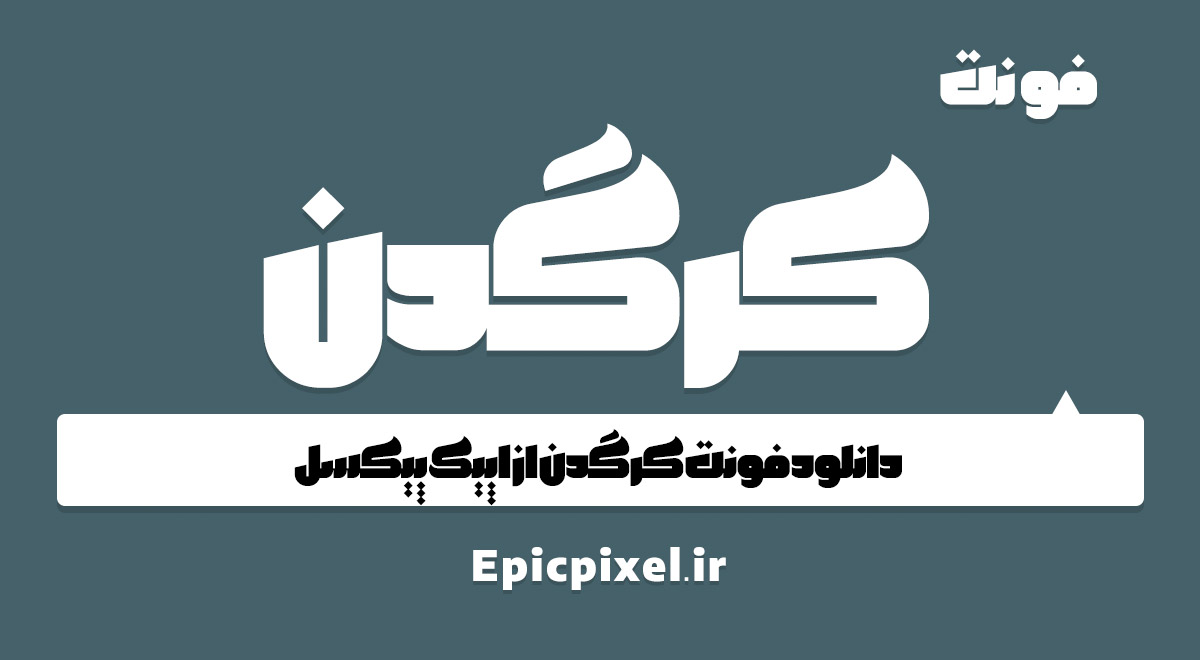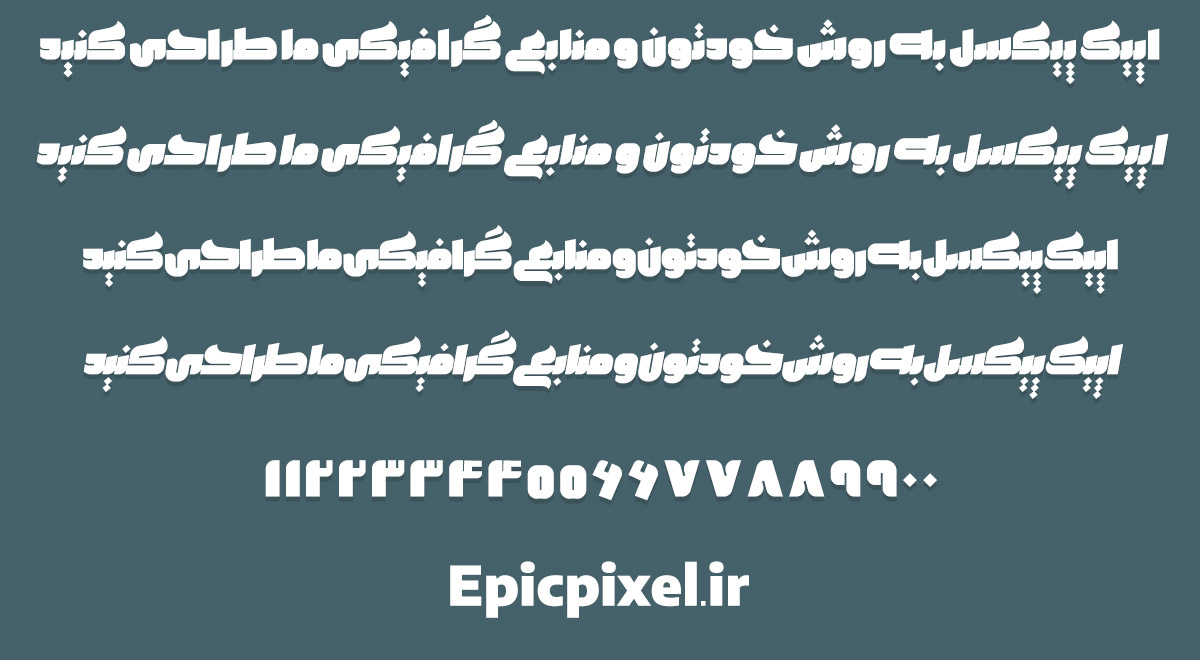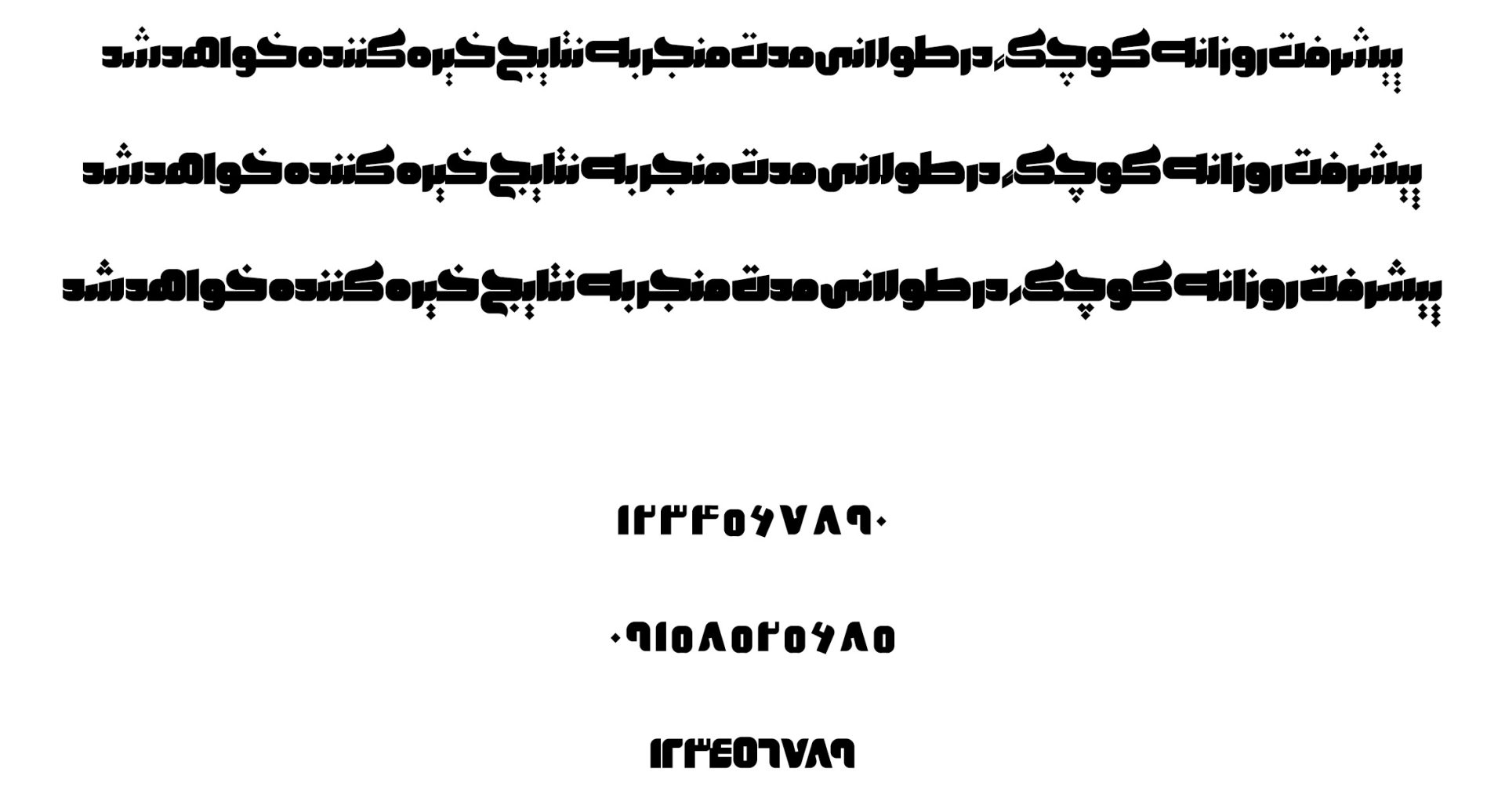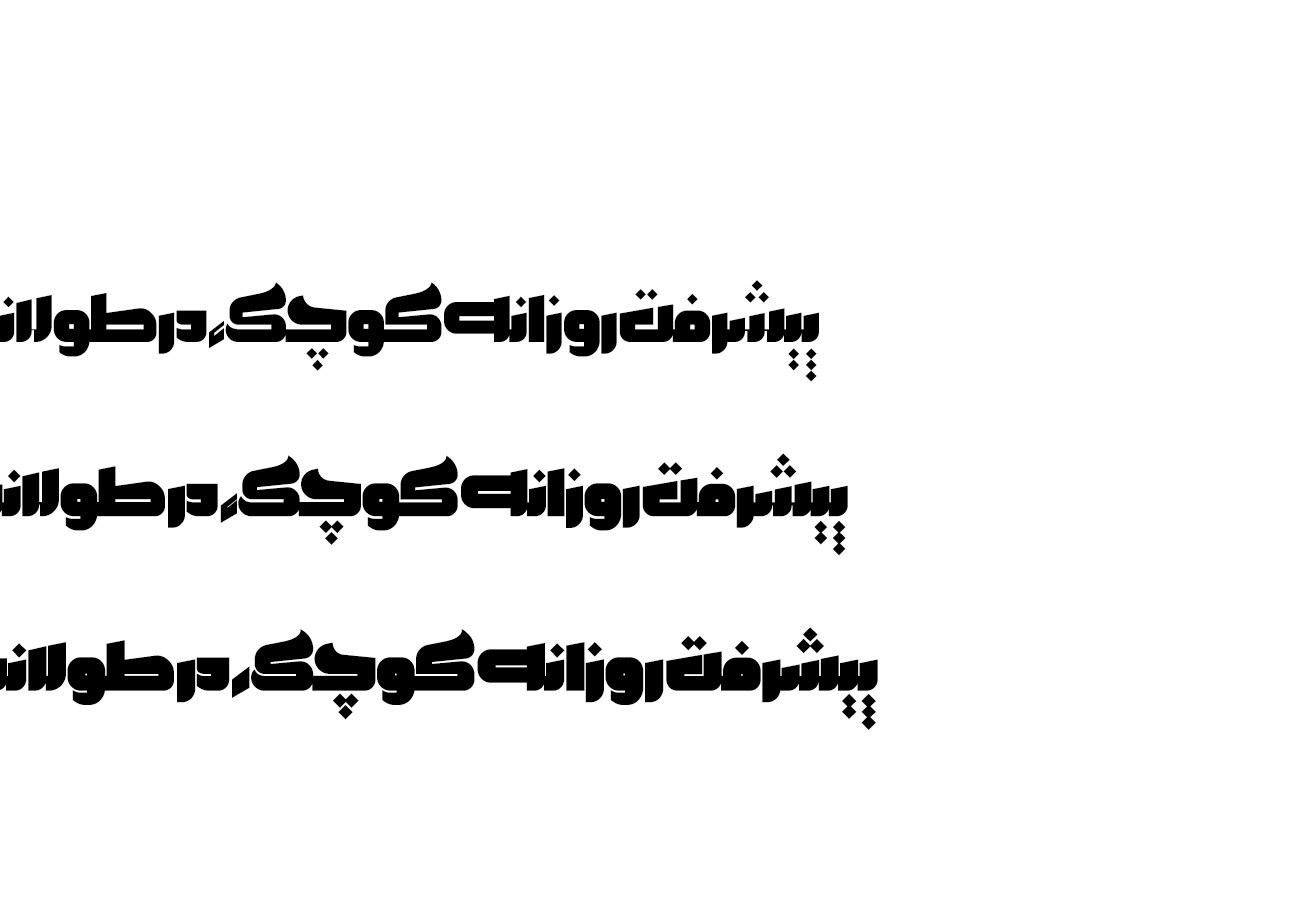
3 فونت کرگدن فارسی
فونت کرگدن فریاد قدرت و اصالت در دنیای تایپوگرافی
فونتهای فارسی زیادند، اما معدودی از آنها با یک نگاه، توجه شما را جلب میکنند و در ذهنتان ماندگار میشوند. فونت کرگدن، یکی از همین فونتهای خاص و جسور است که با الهام از قدرت و اصالت این موجود باشکوه، دنیای تایپوگرافی فارسی را تحت تاثیر قرار داده است. در این مقاله، به سفری در دنیای فونت کرگدن میرویم تا با ویژگیها، کاربردها و تاثیرات آن بیشتر آشنا شویم.
ویژگیهای برجسته فونت کرگدن بیش از یک فونت زیبا
فونت کرگدن، صرفا یک فونت خوشتراش و زیبا نیست؛ بلکه مجموعهای از ویژگیهای منحصر به فرد را در خود جای داده است که آن را از سایر فونتهای فارسی متمایز میکند. برخی از مهمترین ویژگیهای این فونت عبارتند از:
خوانایی بالا: حروف فونت کرگدن، با دقت و ظرافت طراحی شدهاند تا در اندازههای مختلف، خوانایی خود را حفظ کنند. این ویژگی، فونت کرگدن را برای استفاده در طیف گستردهای از پروژههای چاپی و دیجیتال، مناسب میسازد.
هویت مستقل: برخلاف بسیاری از فونتهای فارسی که از فونتهای لاتین الهام گرفته شدهاند، فونت کرگدن کاملا با خطوط و قواعد خوشنویسی فارسی هماهنگ است و هویت مستقل و اصیل ایرانی خود را حفظ کرده است.
تنوع وزنی: فونت کرگدن در وزنهای مختلف (Regular, Bold, Black) ارائه شده است که به طراحان، امکان ایجاد کنتراست و تاکید در متن را میدهد.
مجموعه کامل حروف و علائم: فونت کرگدن، علاوه بر حروف فارسی، شامل اعداد، علائم نگارشی و همچنین حروف ابجد نیز میباشد که کاربری آن را گستردهتر میکند.
کاربردهای فونت کرگدن: فریاد قدرت در عرصههای مختلف
با توجه به ویژگیهای برجستهای که اشاره شد، فونت کرگدن کاربردهای متنوعی در دنیای طراحی گرافیک دارد. برخی از مهمترین کاربردهای این فونت عبارتند از:
طراحی لوگو و نشان تجاری: قدرت و اصالت فونت کرگدن، آن را برای طراحی لوگو و نشان تجاری برندهایی که به دنبال القای حس استحکام، ثبات و اعتماد هستند، مناسب ساخته است.
طراحی جلد کتاب و مجله: فونت کرگدن میتواند با ایجاد حس کنجکاوی و جلب توجه مخاطب، در طراحی جلد کتابها و مجلات، بسیار تاثیرگذار باشد.
طراحی پوستر و تبلیغات: جسارت و پویایی فونت کرگدن، آن را برای استفاده در طراحی پوسترهای تبلیغاتی و ایجاد پیامهای تاثیرگذار، ایده آل کرده است.
طراحی وبسایت و اپلیکیشن: با توجه به خوانایی بالای فونت کرگدن، میتوان از آن در طراحی رابط کاربری وبسایتها و اپلیکیشنها نیز استفاده کرد.
تاثیرات فونت کرگدن فراتر از یک فونت
فونت کرگدن، صرفا یک ابزار طراحی گرافیکی نیست؛ بلکه نمادی از اعتماد به نفس و جسارت طراحان ایرانی در عرصه هنر و طراحی است. انتشار این فونت، به سایر طراحان انگیزه میدهد تا با تکیه بر هویت و فرهنگ ایرانی، به خلق آثار منحصر به فرد و تاثیرگذار بپردازند.
مقایسه فونت کرگدن با سایر فونتهای فارسی در جستجوی تمایز
فونتهای فارسی متعددی وجود دارند، اما فونت کرگدن با ویژگیهای خاص خود، از سایرین متمایز شده است.
چالشهای طراحی فونت کرگدن: سفری پرفراز و نشیب
طراحی فونت کرگدن، مانند هر پروژه خلاقانه دیگری، با چالشهای متعددی روبرو بود. یکی از بزرگترین چالشها، حفظ خوانایی و وضوح حروف در عین جسارت و قدرت بود. همچنین، طراحی فونت با هویت مستقل ایرانی و عدم تقلید از فونتهای لاتین، از دیگر چالشهای این پروژه بود.
آینده فونت کرگدن: رو به سوی قلههای افتخار
فونت کرگدن، با استقبالی که از آن شده است، نشان داده که جایگاه خود را در دنیای تایپوگرافی فارسی به خوبی پیدا کرده است. با توجه به پویایی و خلاقیت طراح این فونت، میتوان انتظار داشت که در آینده شاهد نسخههای جدید و ارتقا یافته این فونت باشیم.
پرسش و پاسخ
فونت کرگدن برای چه نوع پروژههایی مناسب است؟
فونت کرگدن برای طیف گستردهای از پروژهها، از جمله طراحی لوگو، جلد کتاب، پوستر، وبسایت و اپلیکیشن مناسب است.
فونت کرگدن چه تفاوتی با سایر فونتهای فارسی دارد؟
فونت کرگدن با الهام از خطوط و قواعد خوشنویسی ایرانی طراحی شده است و هویت مستقل خود را حفظ کرده است. همچنین، این فونت در وزنهای مختلف ارائه شده و خوانایی بالایی دارد.
آیا فونت کرگدن شامل حروف لاتین نیز میشود؟
نسخه فعلی فونت کرگدن فقط شامل حروف فارسی است، اما در آینده نسخههای جدیدی از این فونت با حروف لاتین نیز منتشر خواهد شد.
با انتخاب فونت کرگدن، به دنیای جسارت و اصالت در تایپوگرافی فارسی قدم بگذارید!